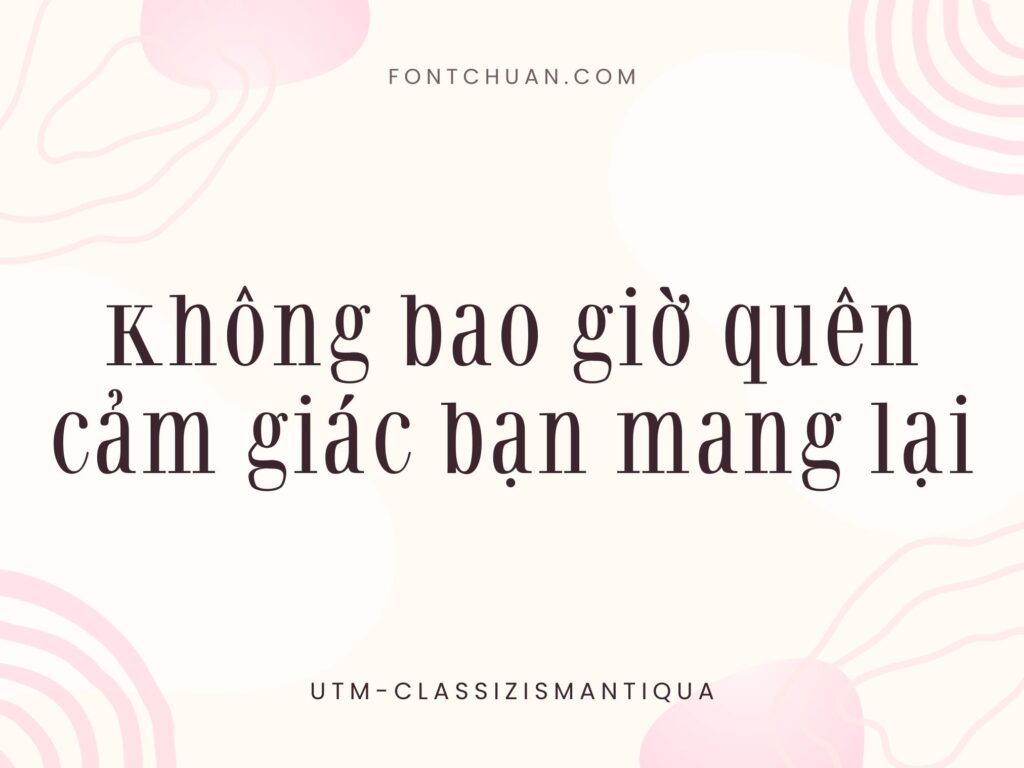
Font UTM Classizism Antiqua Việt Hóa
UTM Classizism Antiqua là phiên bản Việt hóa của font chữ Classizism Antiqua, một kiểu Font Serif cổ điển được thiết kế bởi Manfred Klein. Font này nổi bật với các ký tự có chân thanh mảnh và đường nét tinh tế, tạo cảm giác trang nhã, lịch sự và mang phong cách Font Vintage đặc trưng, gợi nhớ đến các thiết kế in ấn hoài cổ. Phiên bản Việt hóa đã được thực hiện bởi Unicode Thiên Minh, hỗ trợ đầy đủ tiếng Việt cùng hơn 100 ngôn ngữ khác. Đây là một trong những font được cộng đồng thiết kế sưu tầm và chọn lọc nhằm đáp ứng nhu cầu đa dạng trong thiết kế.
UTM Classizism Antiqua có cấu trúc chữ với các nét thanh mảnh và chân chữ rõ ràng, tạo nên sự hài hòa và dễ đọc. Font này phù hợp cho các ứng dụng như thiết kế tiêu đề, văn bản dài, tài liệu in ấn và các ấn phẩm yêu cầu sự trang trọng và chuyên nghiệp. Các ngành nghề như quảng cáo, giáo dục, công nghệ và bất động sản có thể tận dụng UTM Classizism Antiqua để tạo điểm nhấn độc đáo trong thiết kế.